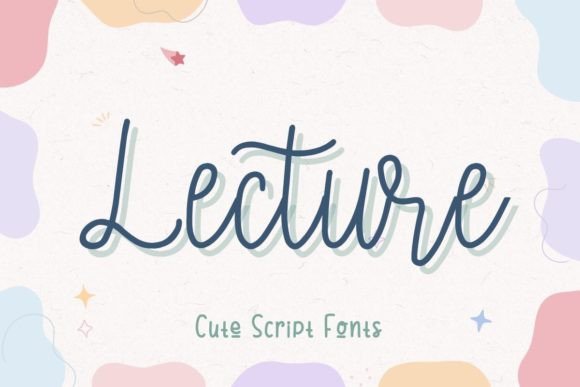
Lecture
適切なデザイン要素を見つけるのは難しい場合がありますが、Lectureは作品を即座に引き立てる優れたコレクションを提供します。
精密に作られたLectureは、クリーンなベクター、滑らかなタイポグラフィ、そして安心のための商用ライセンスを提供します。
POD(オンデマンド印刷)製品、結婚式の招待状、またはソーシャルメディアのグラフィックを作成している場合でも、Lectureは理想的です。